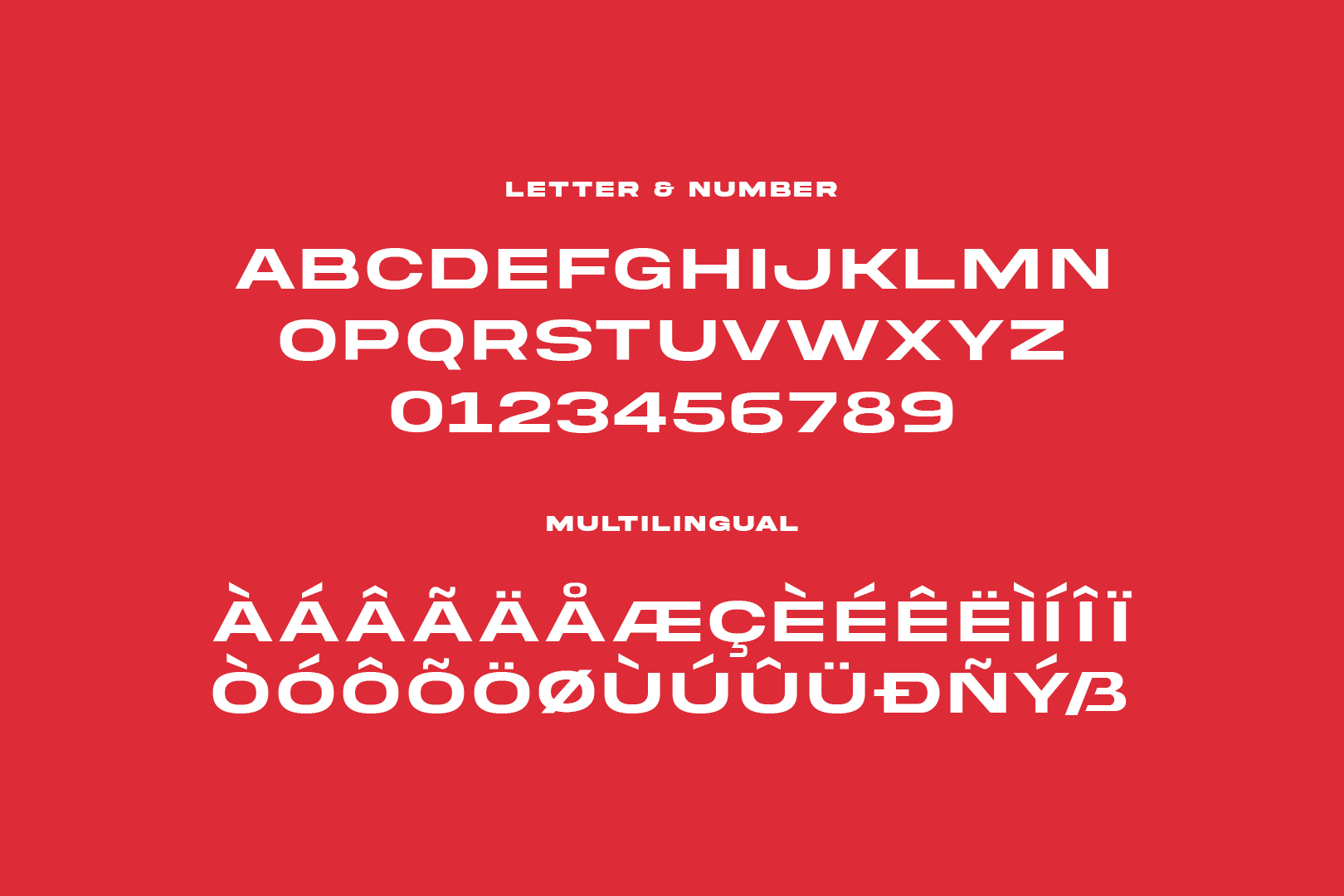
AkiraExpanded可为您的设计带来更丰富和更强烈的印象。使用Abold Style,可使此字体适合作为网站或布局设计的文本/标题。AkiraExpanded还包括使其易于定制的其他字体。MadeFortextDisplay,AkiraExpanded为您的设计带来了时尚感和强烈的印象。使用BoldStyle,使此字体适合作为网站或版面设计的中间文本/标题。AkiraExpanded还包括其他字体,便于您进行定制。